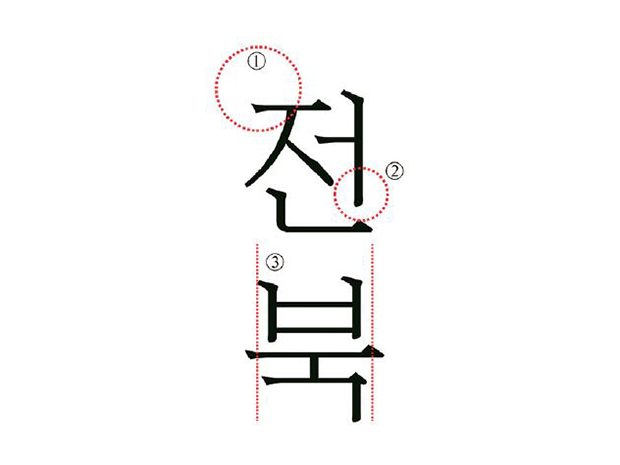
전북일보, 창간 68주년을 맞이해 새로운 서체 공개
올해로 창간 68주년을 맞이한 전북일보가 새로운 고유 서체를 발표했다.
전북일보는 작년 8월부터 글꼴 제작 전문기업인 태시스템과 함께 신문 기사의 가독성과 판독성을 높여줄 본문용 활자의 개발을 시작했다. 태시스템은 전북일보 고유서체 외에도 전주시 공식 글꼴인 ‘완판본 마당체’나 한겨레신문의 ‘한결체’ 등을 제작하기도 했다.
새로운 전북일보의 본문 활자의 특징은 크게 세가지로 볼 수 있는데, 먼저 신문 윤전 인쇄(롤러 형태의 인쇄기를 통해 신속하게 대량으로 인쇄할 수 있는 인쇄 방법) 때에도 글꼴의 형태가 가지런하게 유지될 수 있도록 가로획이 시작하는 부분(①)을 예리하게 디자인 한 부분이다. 다음으로는 세로획이(②) 전체적인 글자의 축이 되어 무게중심을 잡을 수 있도록 강한 인상으로 디자인 된 부분을 볼 수 있다. 마지막으로는 동일한 공간에서도 최대한 크게 글자의 형태(③)가 보일 수 있도록 한 부분이다. 신문 본문의 편집 특성 상 좌우 맞춤 단락에 가득 찬 본문이 서로 조화를 이룰 수 있도록 초성과 종성의 크기를 키웠다.
새로운 활자의 도입과 더불어 전북일보는 5월 31일자 신문부터 본문 활자의 크기도 10.7포인트로 키웠다. 신문 독자는 이전보다 편하고, 또렷하게 기사를 읽을 수 있다. 아울러 기사 제목의 글꼴 또한 더 세련되고 가독성 높은 서체로 변경했다.